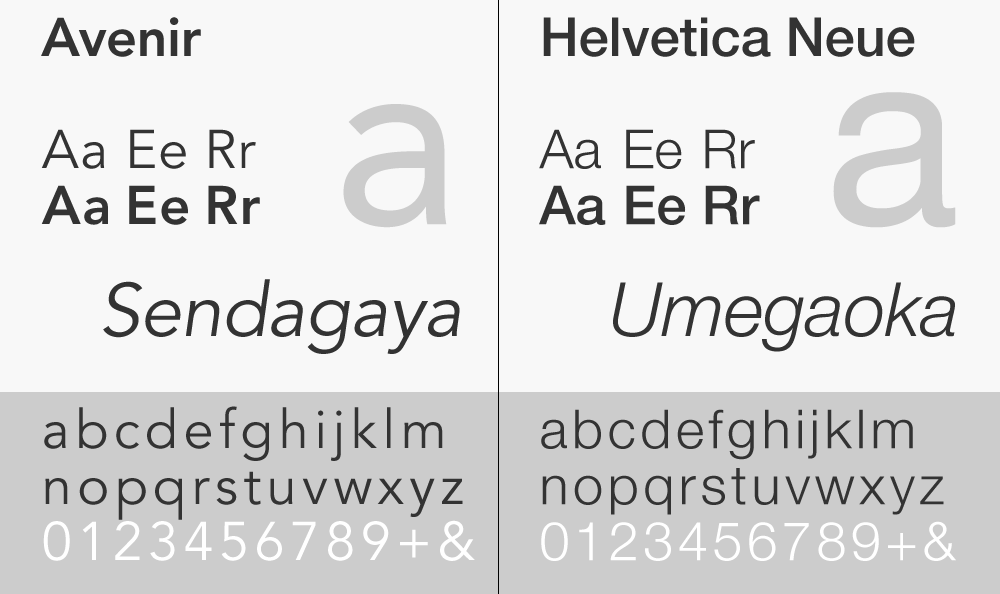
Зачем сайты меняют дизайн шрифтов?
На этой неделе Би-би-си и «Твиттер» выпустили новые шрифты для своих сайтов, спровоцировав противоречивую реакцию пользователей. Почему же шрифты все-таки меняют?
Во вторник многие пользователи «Твиттера» были удивлены изменением шрифта, о котором их не предупреждали заранее. Для некоторых это стало драматичным изменением, пользователи жаловались, что новый шрифт слишком маленький.
«Твиттер», ты сделал огромную крошечную ошибку», — написал один из недовольных новым дизайном.
В четверг сайт спортивной редакции Би-би-си обнародовал собственный шрифт, названный Reith в честь первого генерального директора корпорации.
В конце концов он заменит шрифты Gill Sans, Arial и Neue Helvetica на всех платформах Би-би-си. Новый шрифт должен лучше читаться на маленьких экранах и мобильных устройствах.
Разработать собственный шрифт Би-би-си помог типограф Том Фоули.
Креативный директор компании, разрабатывающей шрифты, Дэлтон Мааг говорит: «[Шрифты] — действительно фундаментальная часть визуальной коммуникации».
«Когда шрифт вам знаком, изменение в деталях на экране создает другой ритм чтения», — убежден Фоули.
Разные шрифты выполняют несколько разные задачи.
Такие разные шрифты
Times New Roman был заказан лондонской Times в 1931 году, после того как дизайнер Стэнли Морисон раскритиковал газету за неразборчивый текст. Впервые новый шрифт появился в газете в 1932 году.
Gill Sans был создан дизайнером Эриком Гиллом в 1928 году, это пример шрифта без засечек. Типограф черпал вдохновение у своего наставника Эдварда Джонстона, который разработал шрифт для лондонской подземки.
Comic Sans был разработан для Microsoft Винсентом Коннаре в 1994 году.
Дизайнер вдохновлялся шрифтами из комиксов.
Helvetica (оригинальное название Neue Haas Grotesk) была создана двумя швейцарскими дизайнерами в 1957 году. Одна из вариаций этого шрифта в настоящее время используется на сайте Би-би-си.
Helvetica — один из самых популярных шрифтов в мире — часто используется в аэропортах, а также в нью-йоркском метро, поскольку это четкий жирный шрифт, который легко прочитать.
Однако это не значит, что он популярен по всему миру. Основатель Dalton Maag Бруно Мааг как-то сравнил его с «дешевым, противным» мороженым.
Мааг и Фоули вдвоем работали над разработкой шрифта BBC Reith.
«Существующие шрифты, которые используются Би-би-си, были разработаны в прошлом веке и хороши для печатных изданий — однако они не всегда достаточно хорошо читаются с маленького экрана — а сейчас мы все гораздо чаще читаем и смотрим что-то на экранах», — говорит главный дизайнер корпорации Колин Бернс.
Новый шрифт уже используется на сайте спортивной редакции Би-би-си
Новый шрифт Reith дебютировал на сайте спортивной редакции Би-би-си, пока мнения на счет него разделились.
Один из читателей написал: «Мне он кажется инфантильным, и не слишком ли он жирный?».
«Новый шрифт ужасен, он выглядит дилетантским. Я думал, что оказался на фальшивом сайте, когда открыл «Би-би-си Спорт», именно так он сейчас выглядит», — написал другой.
«Обычно не люблю перемены… Однако сделаю исключение для этого случая: эти перемены мне подходят», — не согласился с критикой читатель Би-би-си.
Изменения на сайте спортивной редакции в итоге распространятся на все платформы Би-би-си.
Однако культовые кубики с буквами BBC (шрифта Gill Sans) останутся на своем месте.
Би-би-си не единственное СМИ, которое разработало собственный шрифт. Times New Roman, привычный для пользователей Microsoft Word, был создан в 1932 году для британской Times.![]()
Когда газета Guardian меняла свой дизайн в 2005 году, у нее также появился собственный шрифт — Guardian Egyptian.
Кроме того, у транспортной системы Лондона есть собственный шрифт под названием Johnston, который используется с 1916 года.
Автор фото, Getty Images
Подпись к фото,У транспортной системы Лондона есть собственный шрифт под названием Johnston
Новый шрифт не только будет легче читаться с экранов, но и позволит Би-би-си сэкономить деньги.
Сейчас организация платит за лицензию на использование шрифтов Gill Sans, Arial и Neue Helvetica.
Дизайнер шрифта получает комиссию от использующих его компаний, издателей и организаций.
«Обычно стоимость лицензии зависит от того, как много у вашего сайта уникальных посещений в месяц. Исходя из их количества стоимость для Би-би-си может быть огромной», — считает графический дизайнер Дэвид Эйри.
«Организация может сделать единовременную выплату для использования шрифтов на длительный срок, однако это будет очень большая сумма», — добавляет он.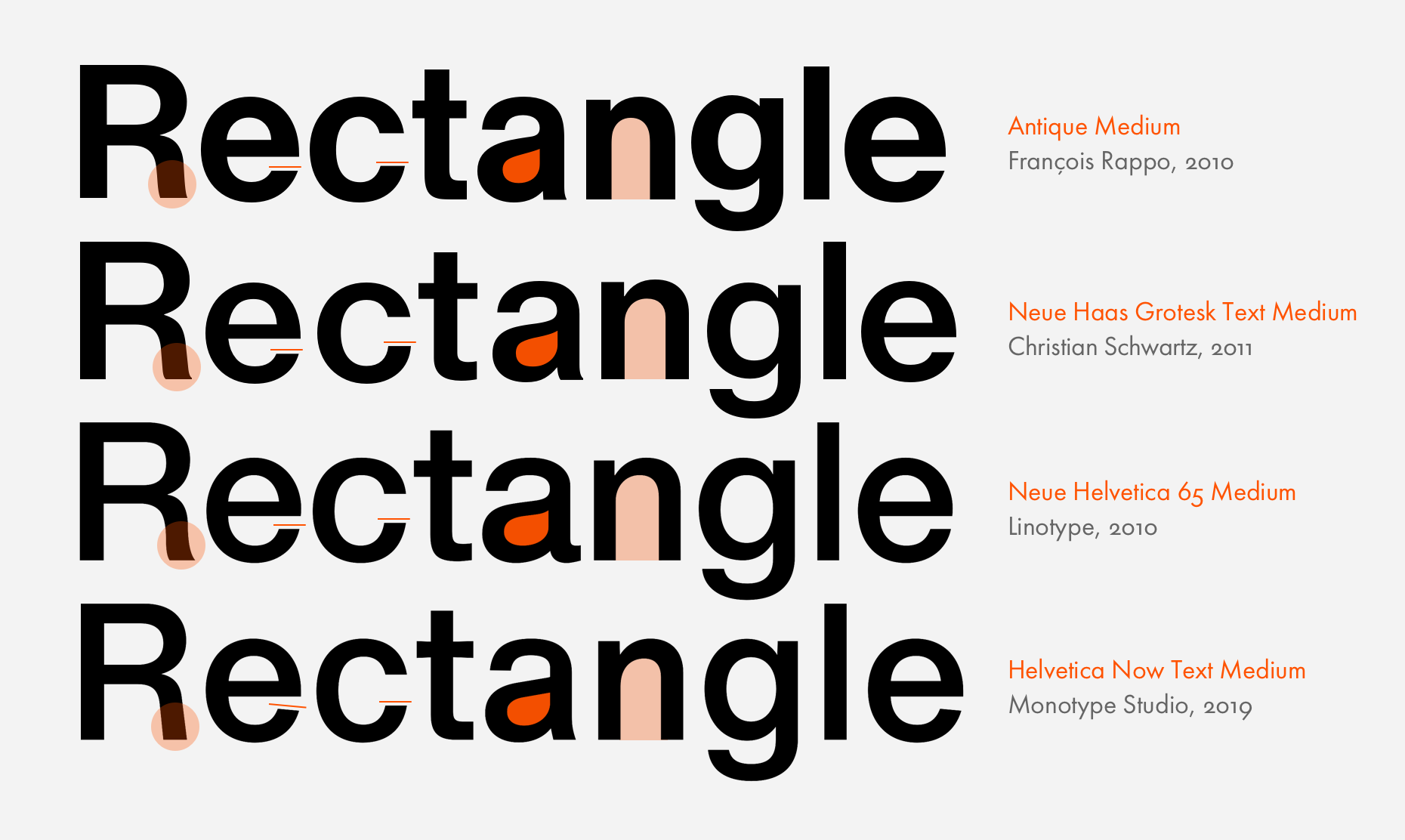
Би-би-си не уточняет, сколько денег сейчас тратит на лицензии, однако говорит, что появление собственного шрифта приведет к «существенной экономии».
Helvetica vs. Arial: вы знаете в чем разница?
Helvetica и Arial – это имена двух шрифтовых гарнитур, известных практически каждому дизайнеру. А также многим непрофессиональным пользователям компьютеров.